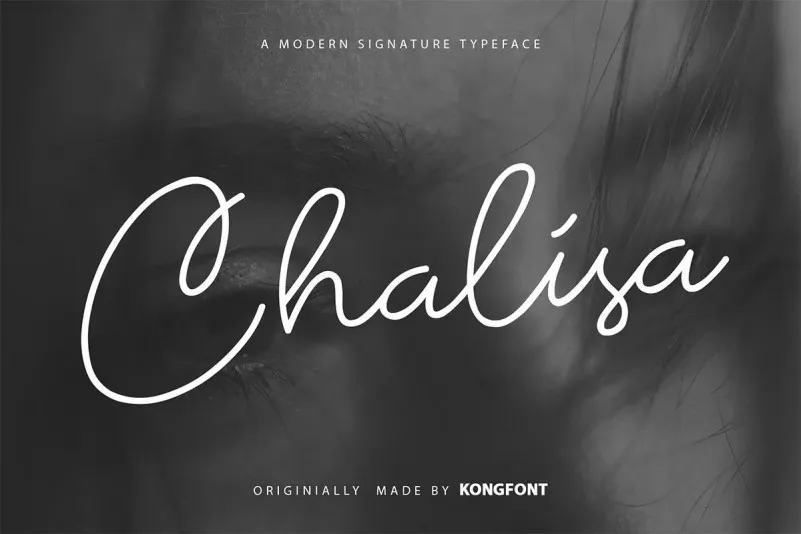
Chalisa Font – Fonte Grátis
Chalisa Font
A Chalisa Font é uma elegante tipografia script moderna, com linhas monolineas bem equilibradas que tornam-a ideal para diversas aplicações. Suas letras perfeitamente balanceadas a tornam uma opção preferencial para designers buscando uma fonte personalizada e contemporânea. A Chalisa é um recurso versátil para criar identidades visuais: desde selos para cartas até logotipos, materiais de embalagem, rótulos ou até mesmo para adesivos em eventos sociais como casamentos. Seja para o seu próximo projeto editorial, seja ele uma notícia diária ou um post publicitário, a Chalisa tem tudo que você precisa para dar ao seu design aquele toque autêntico e único. Trazendo estilo com sofisticação, esta fonte em forma de letra escrita à mão é mais do que apenas um recurso gráfico: ela é uma peça chave na sua estratégia visual.